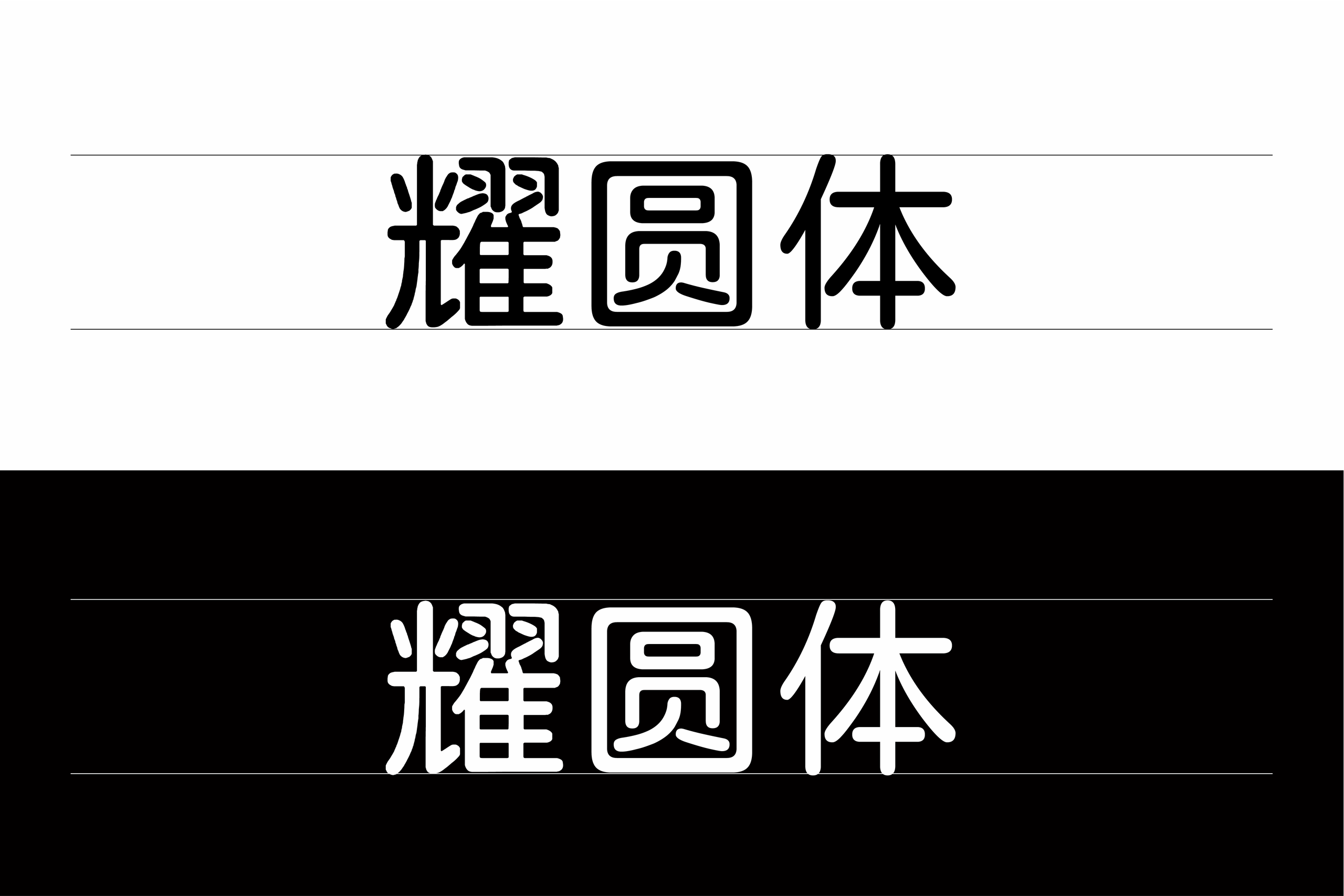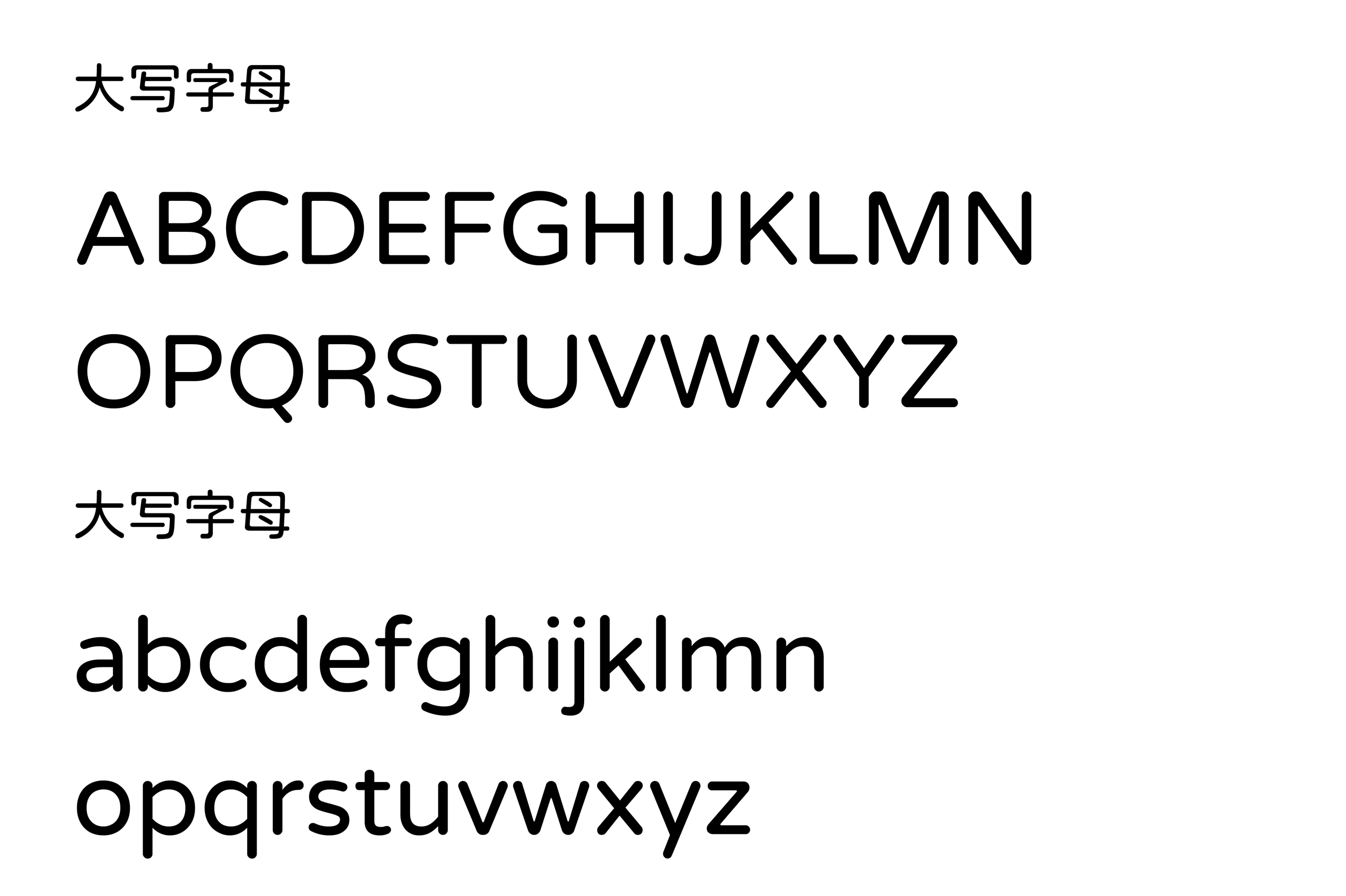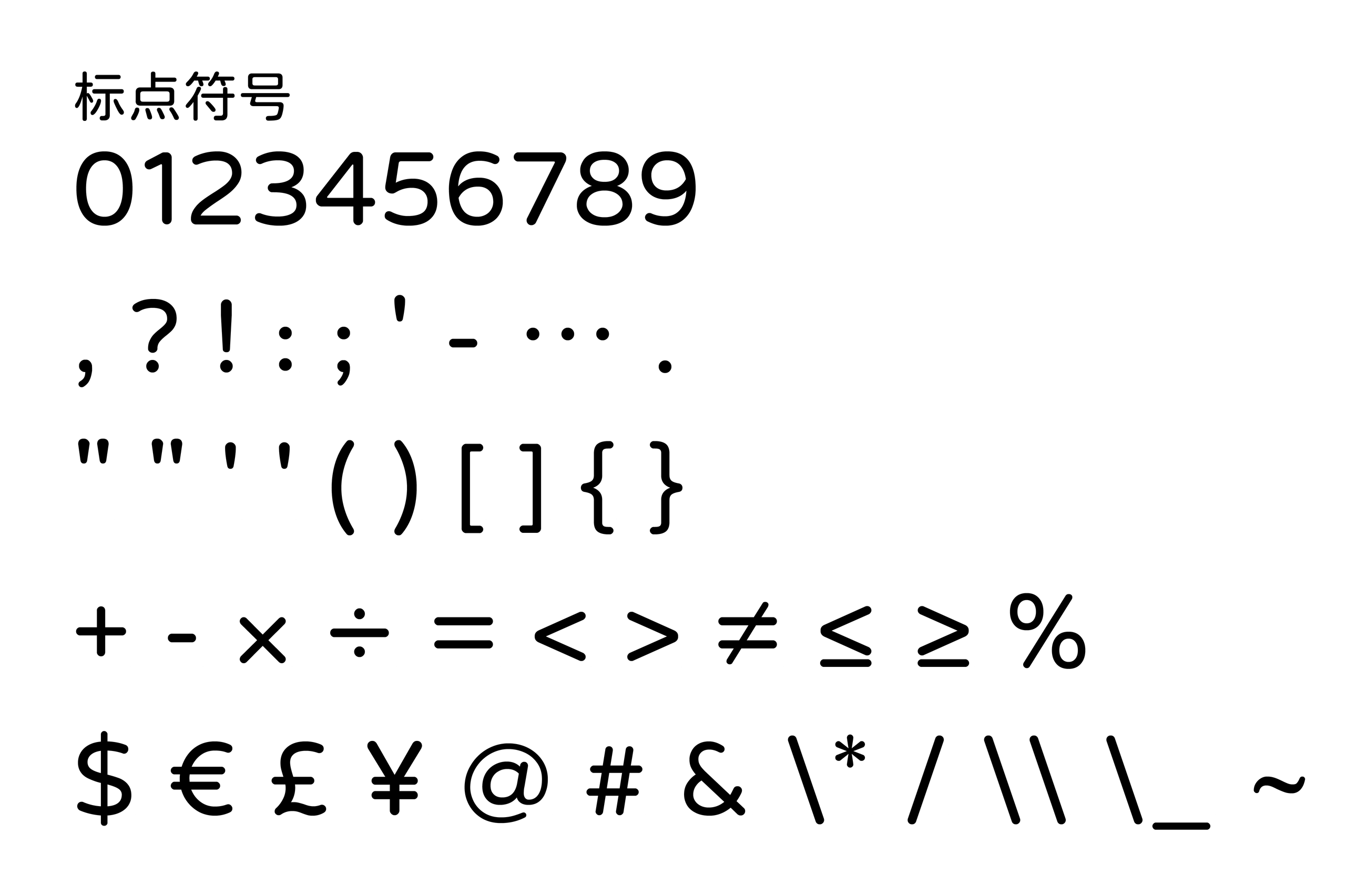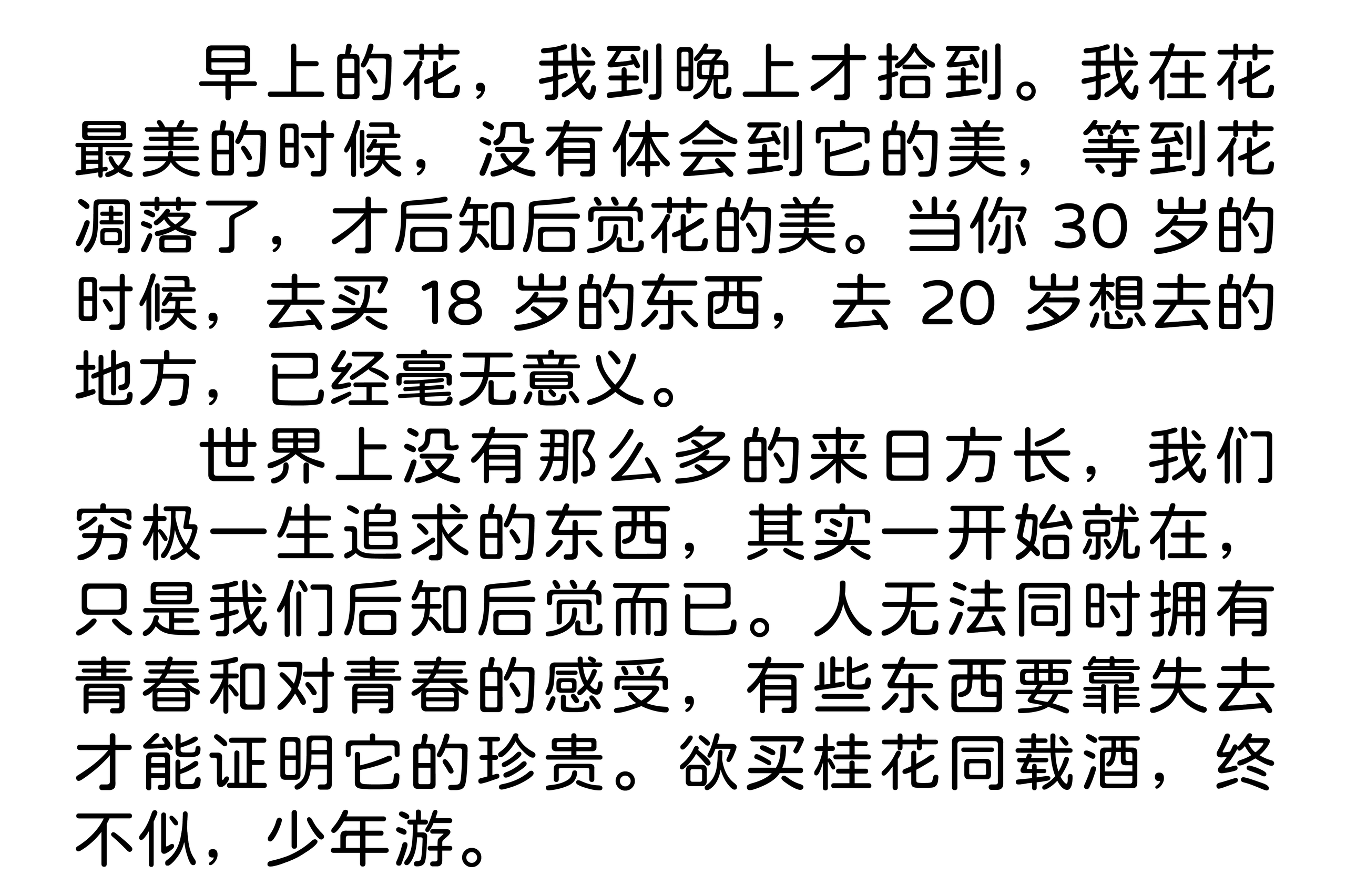
耀圆体
耀圆体 Kirakara Maru 是一款以圆润、简洁为主要视觉特征的中文圆体字体。字体整体采用柔和的圆角笔画,将中文黑体原本较为硬朗的结构进行圆润化处理,使字形呈现出轻盈、自然且具有亲和力的视觉效果。
耀圆体在字形设计上以寒蝉全圆体作为目标风格,并参考思源黑体 CN的文字结构,在保持汉字基本结构与识别性的同时,对笔画转折、收笔以及字面轮廓进行了更加柔和的处理。从展示效果来看,字体具有比较明显的几何感,横竖笔画简洁利落,圆角处理则让整体视觉少了一些传统黑体的严肃感,多了一份轻松和现代气息。
这款字体的中文部分具有较强的视觉统一性,尤其是在较大字号下,圆润的笔画轮廓能够得到更加充分的展现。部分字形采用较为简化的结构处理,使文字整体看起来更加轻巧,同时也形成了耀圆体独特的字体个性。
除了中文字符之外,耀圆体还配套设计了英文字母、数字及常用标点符号。英文字母采用简洁的无衬线结构,大写字母线条舒展,小写字母则呈现出更加圆润自然的形态;数字与标点符号同样延续了整体圆角化的设计语言,使中文与英文、数字进行混排时能够保持较好的视觉一致性。
在实际设计中,耀圆体适合用于海报标题、品牌视觉、包装设计、网页设计、社交媒体配图、活动宣传以及文创设计等场景。圆润的字形能够为画面带来更加轻松、年轻的视觉氛围,尤其适合需要表现亲和力和现代感的设计作品。
总体而言,耀圆体 Kirakara Maru 是一款具有鲜明圆润特征的中文圆体字体。它以简洁的黑体结构为基础,通过圆角化的笔画设计赋予文字更加柔和、轻松的视觉表现,在保证基本识别度的同时,也具有较强的设计感。对于需要免费商用中文圆体、圆润字体、可爱简洁字体的设计项目而言,耀圆体是一个值得尝试的选择。